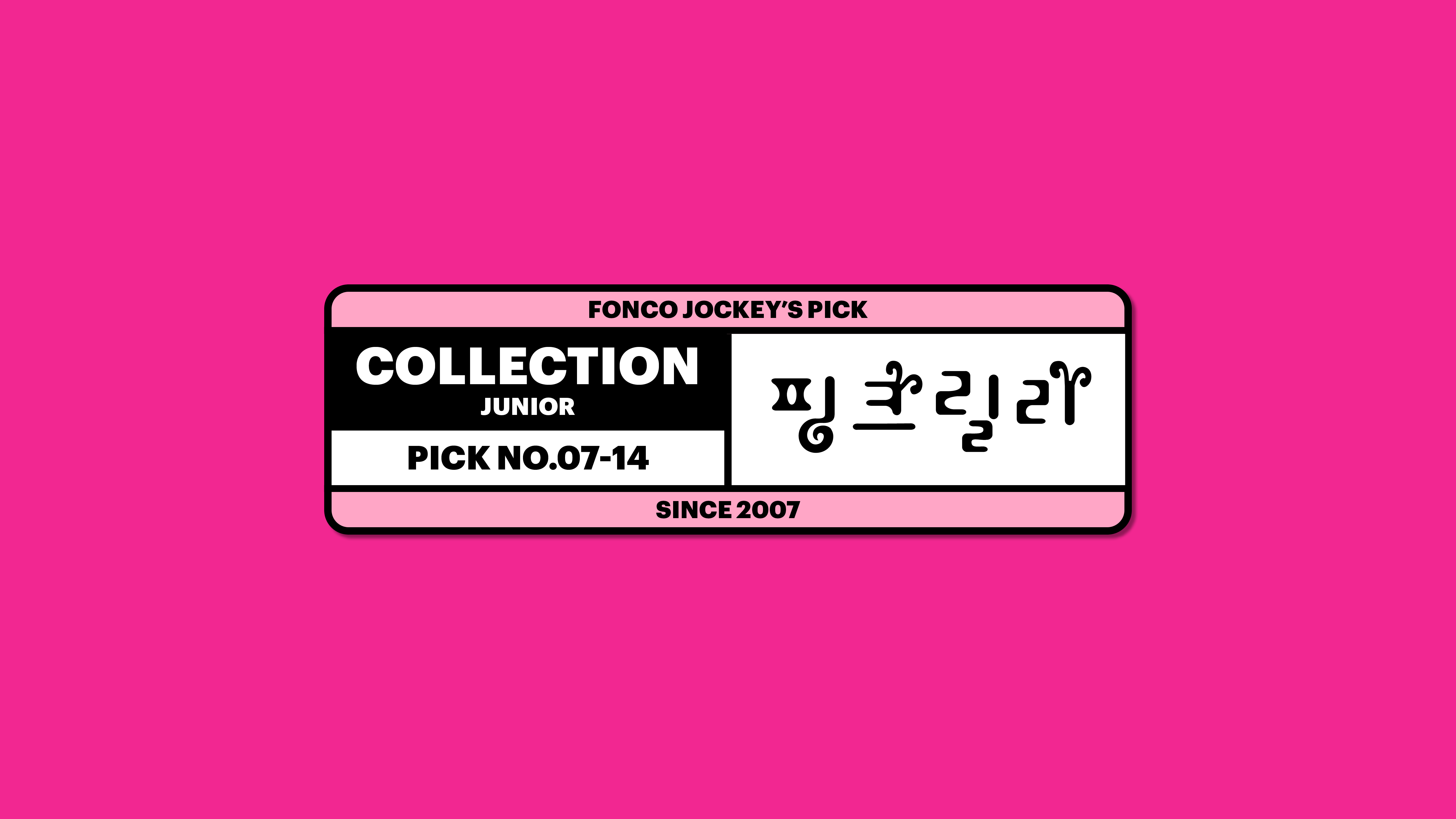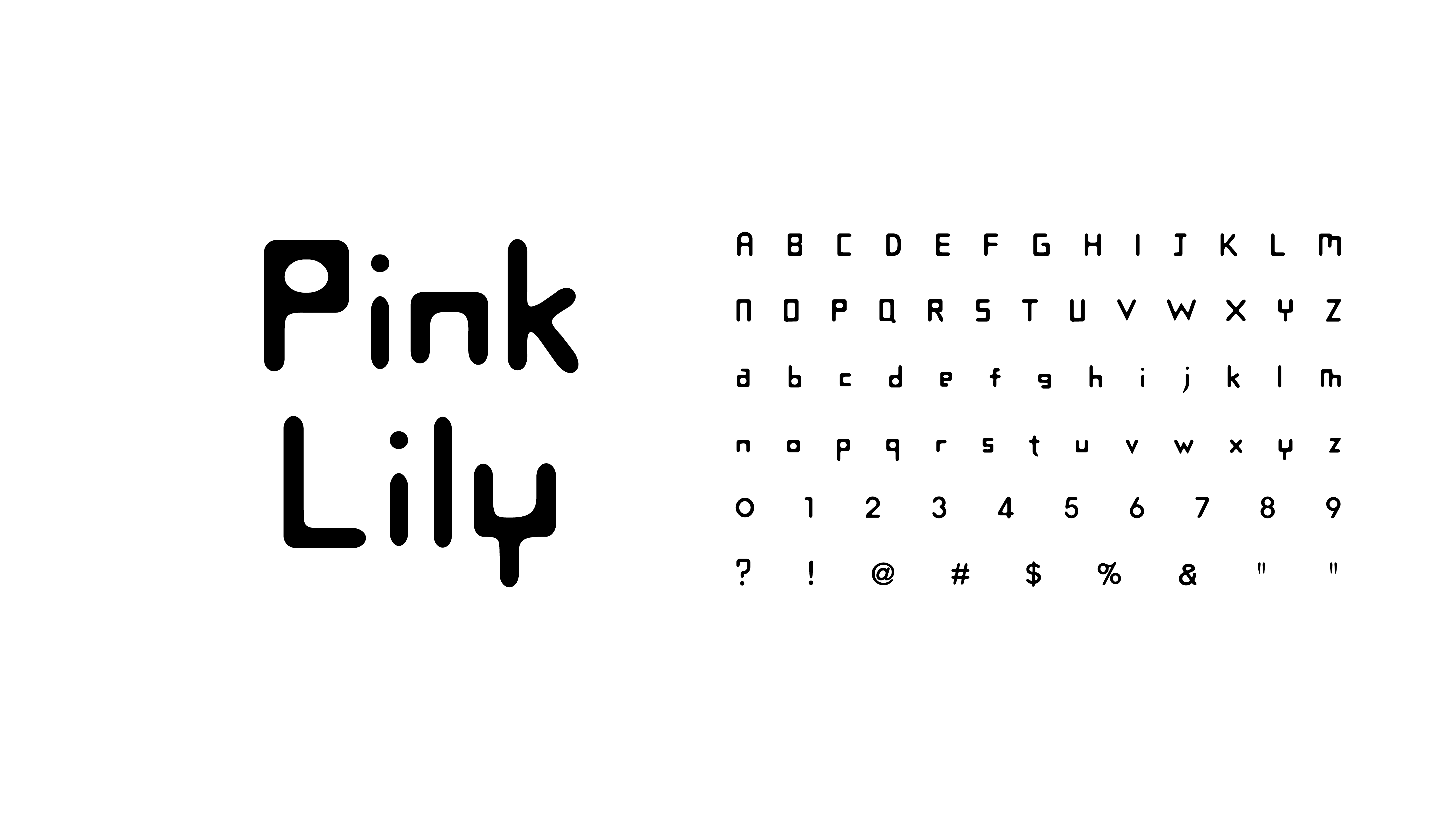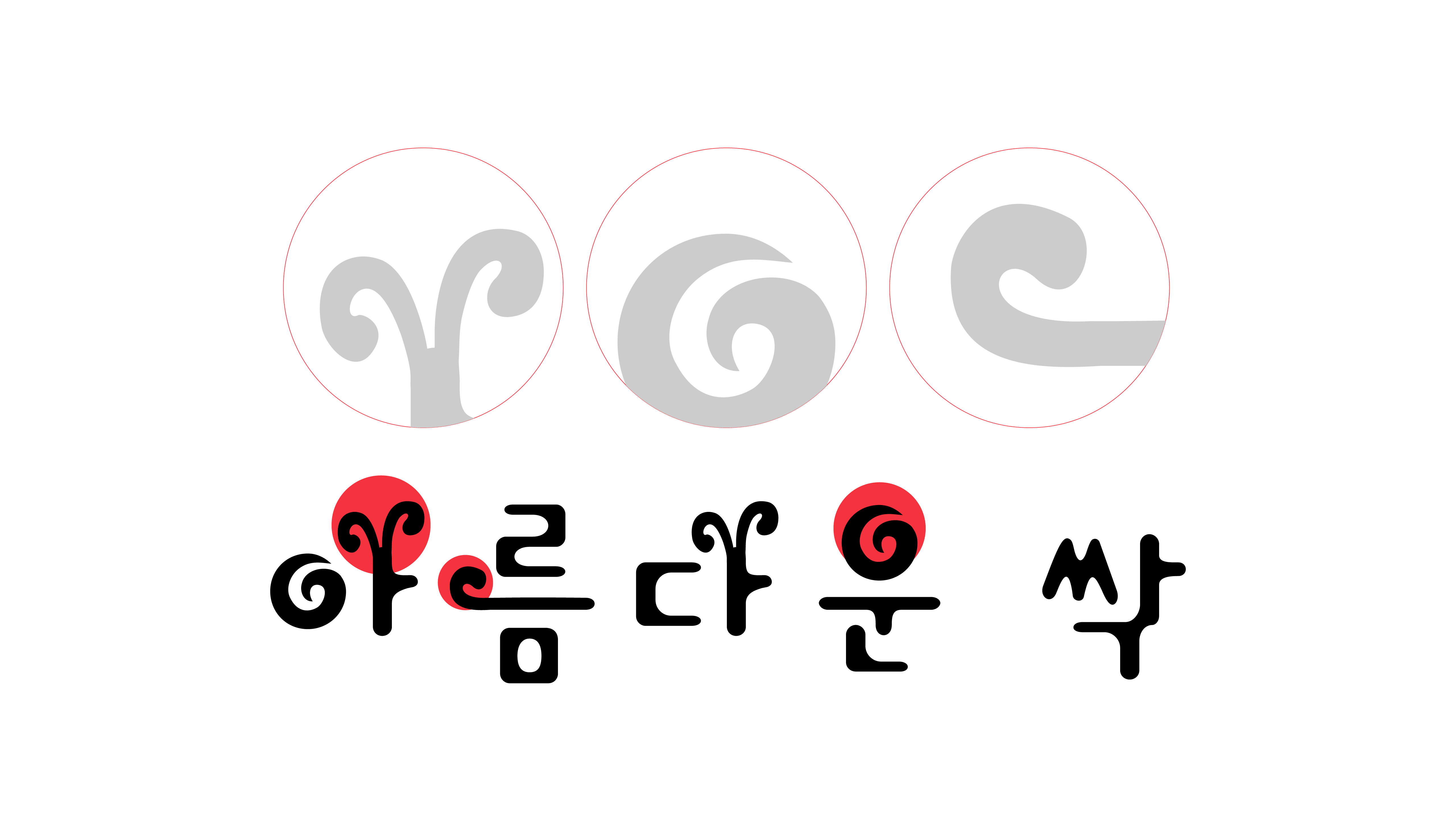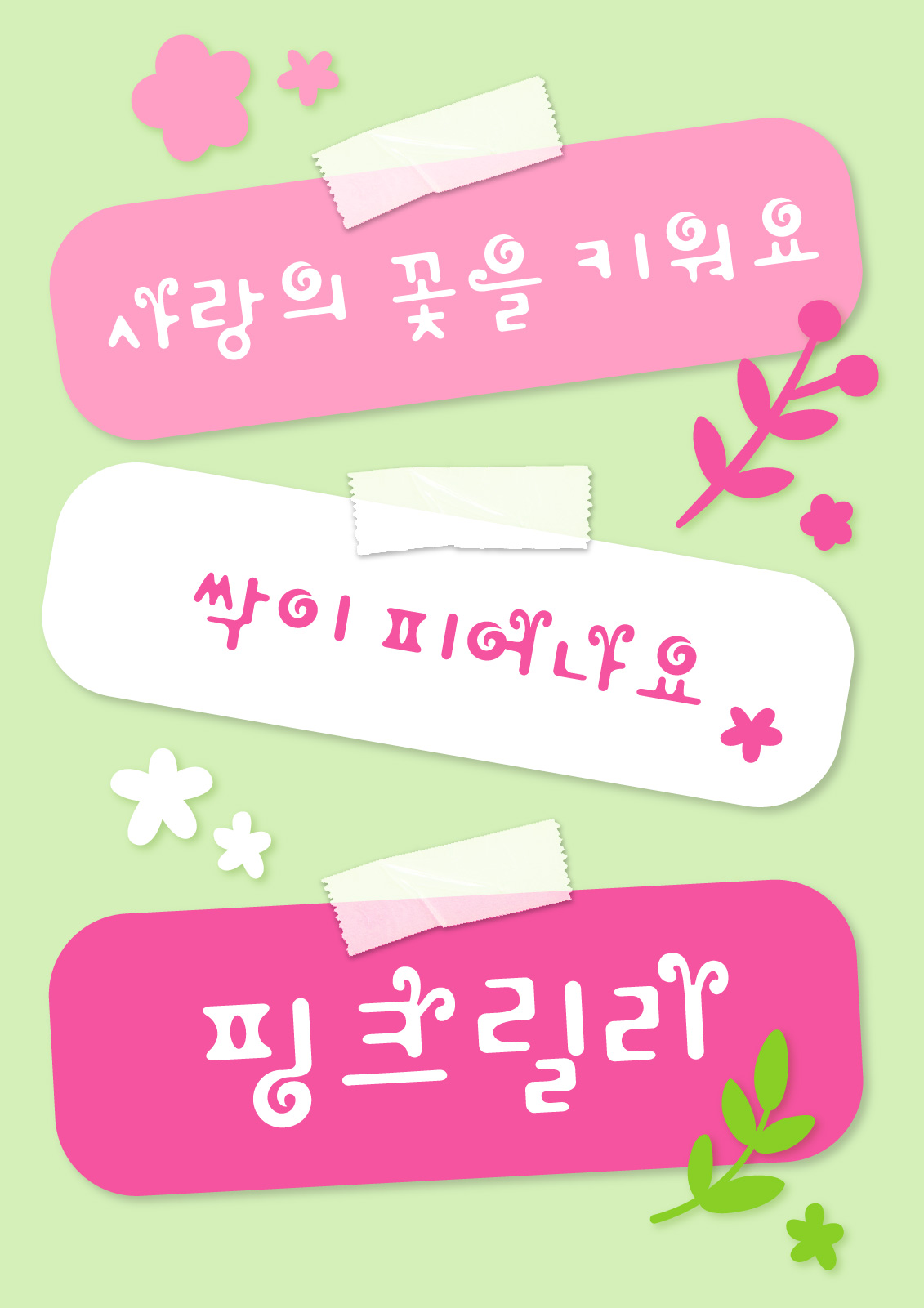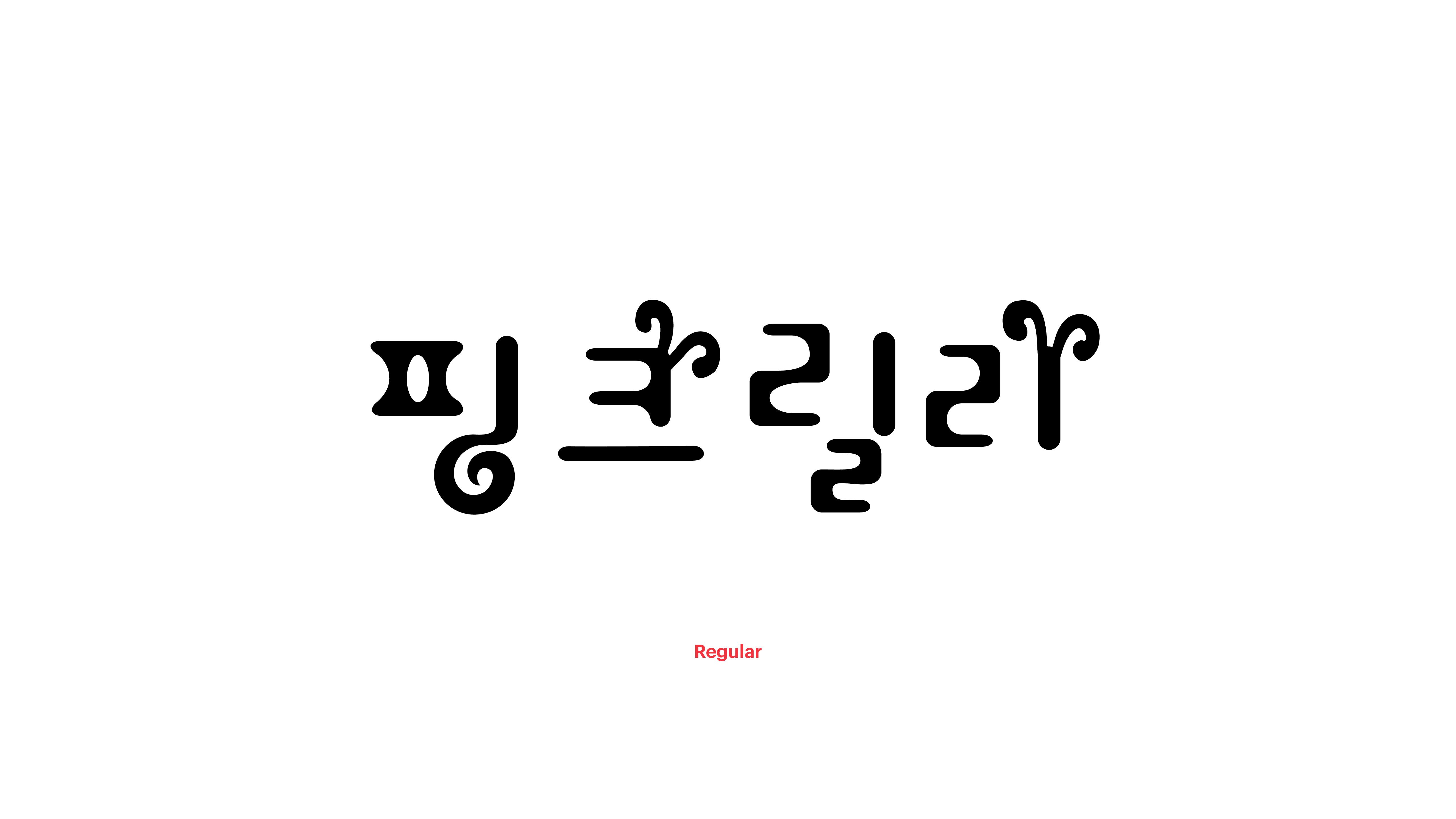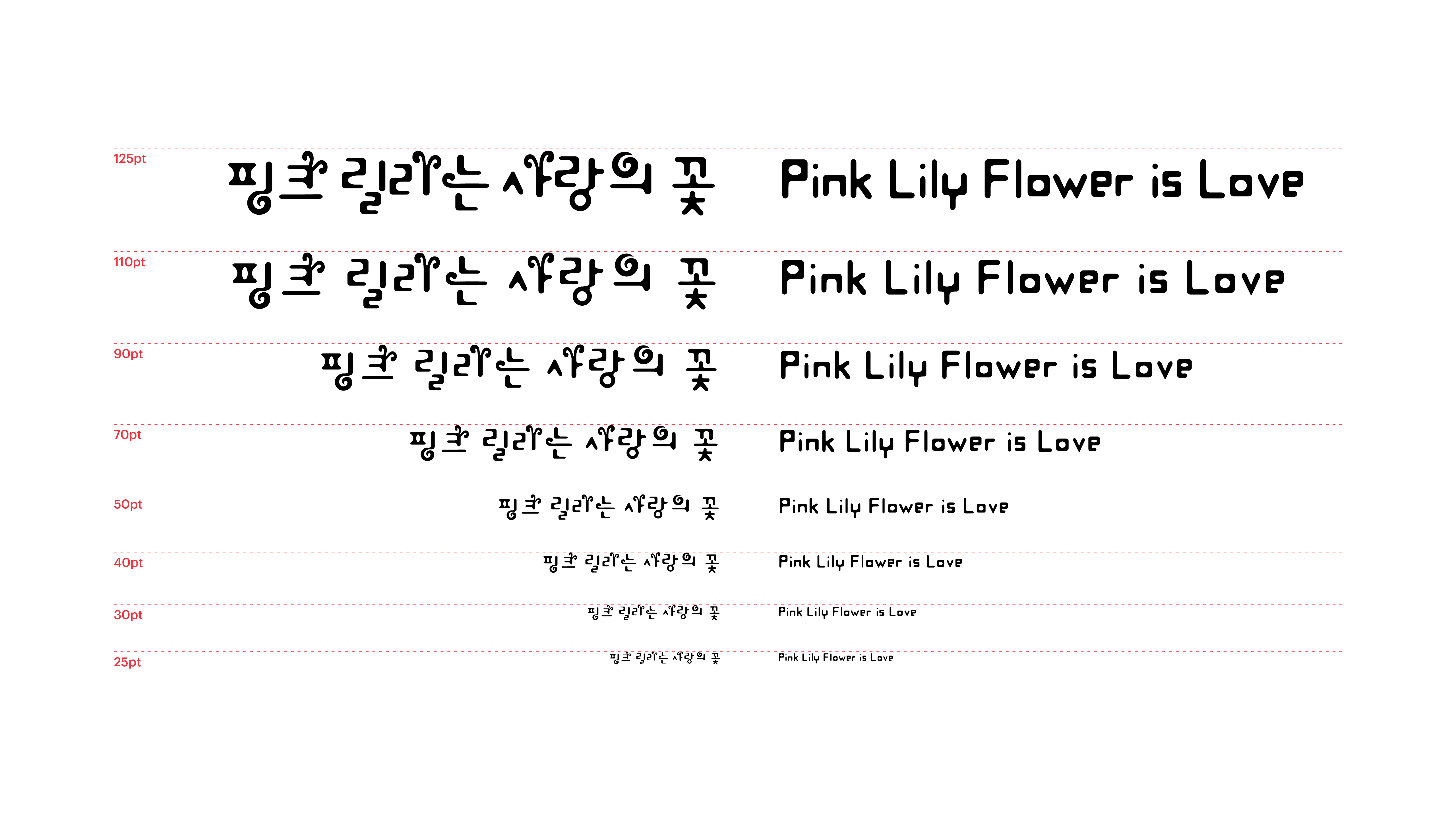
핑크릴리
Yoon 핑크릴리
핑크 릴리는 식물의 곡선을 떠올리게 하는 신비한 폰트입니다. 모음에서 아름다운 싹과 꽃이 피어나듯 부드러운 라인이 펼쳐지지요. 아직은 작은 씨앗 단계이지만 무럭무럭 키워가고 싶은 생각들이 있으신가요? 그렇다면 핑크릴리체로 씨, 씨, 씨를 뿌리듯, 차근차근 적어보는 거 어떨까요?